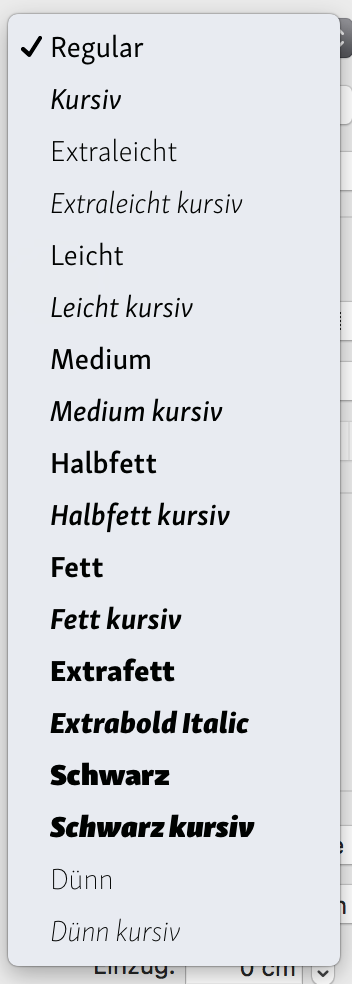
Deutsche Bezeichnungen für Strichstärken etc.
Unicode CLDR liefert Lokalisierungen von Zahlenformaten und Übersetzungen für viele Begriffe, die in GUIs von unterschiedlichen Softwareprodukten verwendet werden. Vor allem wegen variablen Fonts wurden kürzlich auch Einträge für einige absolute Strichstärken hinzugefügt. Traditionell erfolgt die Benennung der angebotenen Schriftschnitte eher relativen Gesichtspunkten, außerdem inzwischen häufig auf Englisch. Dort sind im oberen Bereich recht häufig Heavy und Black anzutreffen, wofür als deutsche Entsprechung meist extrafett und ultrafett dienen. In CLDR sind die allerdings schon vergeben und dürfen nur für denselben numerischen Wert identisch sein. Man könnte über die englischen Zuordnungen zu Zahlenwerten streiten, aber die sind inzwischen vorgegeben.
Die aktuellen Werte sind in der folgenden Liste kursiv hervorgehoben. Allerdings dürfen regular und medium nicht beide mit normal übersetzt werden, während black und heavy dieselbe deutsche Bezeichnung haben dürften.
• 100 thin: dünn (ultramager?)
• 200 extra-light: extramager
• ultralight: ultraleicht (?, extramager?)
• 300 light: mager
• 350 semilight: halbmager
• 380 book: Buch (?, Werk?)
• 400 regular: normal (regulär?)
• 500 medium: normal (leichthalbfett?, kräftig?, mittel?)
• 600 semibold: halbfett
• 700 bold: fett
• 800 extra-bold: extrafett
• 900 black schwarz (?)
• heavy: ?
• 950 extra-black: extraschwarz (?, ultrafett?)
• ultrablack: ultrafett
• ultraheavy: ultrafett
Wie würdet ihr vor allem 400 und 500 sowie 900 und 950, ggf. samt Synonymen, benennen? Sind schwarz und extraschwarz in Ordnung oder lieber ultrafett und x (oder andersrum)?
Wie würdet ihr vor allem 400 und 500 sowie 900 und 950, ggf. samt Synonymen, benennen?
Unter welcher Zielstellung? Für Laien verständlich … historisch verwendet … möglichst systematisch … – da gibt es viele Möglichkeiten.
Verständlich für Menschen, die eine Deutsch lokalisierte Software verwenden, die diese feine Unterscheidung anbietet, also eher Fortgeschrittene und Experten, und dabei so systematisch wie möglich.
Ich habe bspw. schwarz in diesen Zusammenhang noch nie gesehen und frage mich, ob das als schlechte Direktübersetzung von black wahrgenommen werden würde.
Durch die Zwischenstufen werden es mehr als alle mir bekannten Systeme haben. Ich versuch’s trotzdem mal:
• 100 ultramager (oder extrazart)
• 200 extramager (oder zart)
• 300 mager
• 350 halbmager
• 380 Buch
• 400 normal
• 500 halbfett
• 600 dreiviertelfett
• 700 fett
• 800 extrafett
• 900 schwer
• 950 extraschwer
Bleisatzkollegen werden protestieren, da das mit früheren Bezeichnungen nicht übereinstimmt. Aber im Digitalkontext sollte es in Ordnung gehen und die englischen Begriffe geben ja zwingend die Anker vor. Da muss man dann auch dabei bleiben, sonst stiftet es nur Verwirrung, wenn Book nicht Buch ist oder Bold nicht Fett.
Da muss man dann auch dabei bleiben, sonst stiftet es nur Verwirrung, wenn Book nicht Buch ist oder Bold nicht Fett.
Geht mir allerdings jetzt bei diesen so:
• 500 halbfett
• 600 dreiviertelfett
Geht mir allerdings jetzt bei diesen so:
Tja. Die englische Vorgabe ist: medium • semibold • bold.
Wenn man bei fett landen will, muss entsprechend eingeteilt werden. Halbfett und dreiviertelfett schaffen das und sind schon im Bleisatz benutzte und auch außerhalb der Schriftwelt angewandte Begriffe.
eine Deutsch lokalisierte Software
Muss denn überhaupt auf teufelkommraus lokalisiert werden? Software übersetzt Du ja auch nicht mit Weichware oder durchgängig mit Programm (das als Begriff von App abgelöst wird im Moment). Medium muss imo überhaupt nicht lokalisisert werden. Die restlichen Begriffe wüde ich auch nicht übersetzen, da diese durchaus den Status eines terminus technicus haben können. Im deutschsprachigen Raum sind thin und light auch allgegenwärtig, so dass da die Bedeutung klar sein dürfte.
Wäre es ein Ansatz, auf Benennungen zu verzichten und stattdessen die Nummern zu verwenden?
Kein Hersteller wird gezwungen, seine Software zu lokalisieren oder dafür CLDR bzw. ICU zu verwenden, aber viele nutzen diese Ressourcen, was zu einer gewissen Einheitlichkeit führt und eventuelle Verbesserungen oder Korrekturen können zentral erfolgen. Ebenso können viele Nutzer die Sprache ihres Betriebssystems oder ihrer Anwendungssoftware im Rahmen des Verfügbaren frei wählen.
Da das Ziel dieser Begriffe offenbar ist, den zugrundeliegenden Zahlenwerten freundlichere Namen zu geben, sind numerische Label ungeeignet. Je nach Software sind die entsprechenden Werte ja trotzdem verfügbar.
Es ging mir nicht um das Lokalisieren an sich, es ging mir um das Lokalisieren gut gelittener und weit verbreiteter termini technici. Und wenn man Zahlen freundlichere Namen geben möchte, sollte man -- so finde ich -- bei den üblichen Begriffen bleiben. So lange mein Font XXX light.otf heißt und bei Myfonts (oder Dienst Deiner Wahl) als XXX Light ausgezeichnet wird, sind die angelsächsischen Begriffe imo einer zwanghaften Verdeutschung vorzuziehen, zumal diese Lokalisierung zumindest teilweise auf historische Bilder zurückgreift, die heute der <vorurteil>Mehrheit</vorurteil> der Anwender fremd sind.
Pages bietet da für Skolar Sans offensichtlich die wörtlich ins Deutsche übersetzten, eingangs zitierten englischen Begriffe für die Hunderterschritte an, wobei dann auch regulär und mittel (sowie natürlich extrafett kursiv) zu erwarten gewesen wären.
Vielleicht weil wir die Vokabeln medium und regular auch im Deutschen finden? Sind ja immerhin schon ein mehr als zweitausend Jahre in unserer Geographie verbreitet...